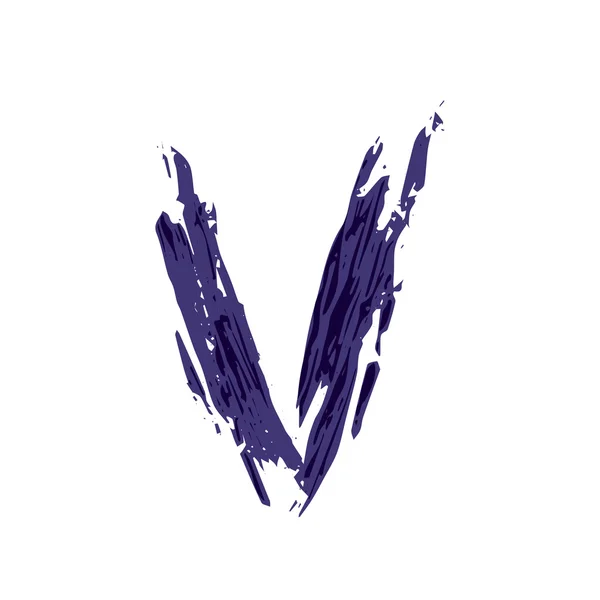
таких однородных букв на разных конструктивных началах нарушает
весь стиль шрифта независимо от того, по какому принципу скон¬
струированы все остальные буквы с округлыми элементами.
Как известно, уже в эпоху Возрождения создавалось много трак¬
татов по конструированию шрифтов разных рисунков и стилей. Осо¬
бое внимание по праву обращалось на шрифты типа антиквы. В дан¬
ной книге приведены некоторые образцы конструирования букв
великими мастерами прошлого. В дополнение к ним дается несколько
других примеров, исполненных с учетом как опыта мастеров прош¬
лого, так и практических требований современности.
abcdefßhijk Im
abcdef&h ijkt
Два принципа исполнения шрифта — два типа инструментов. Вверху — шрифт,
написанный ширококонечным пером, внизу — рисованный шрифт.
В соответствии с этим расположены и орудия выполнения:
1 — гусиное или тростниковое перо; 2 — металлическое ширококонечное перо;
3 — ширококонечное перо для выполнения крупного шрифта; 4 — плоская
кисть; 5 — перо из дерева; 6 — тонкое перо; 7 — остроконечная кисть;
S — игла; 9 — штихель
Наиболее распространенный способ конструирования шрифта —
построение букв в квадрате.
Для примера составим конструкцию ан¬
тиквы. Прежде всего установим, какую часть стороны квадрата зай¬
мет основной штрих, т. е. определим светлоту шрифта. За толщину
основного штриха примем Vio стороны квадрата. Это будет единицей
измерения основного штриха для всех букв алфавита. Затем разде¬
лим все стороны квадрата на 10 равных частей и вычертим сетку. Она
поможет конструировать буквы и следить за расположением отдель¬
ных элементов. Толщина соединительных штрихов составляет опре¬
деленную часть толщины основного штриха, например, Ч->, ‘/з и т. д.
В настоящей книге помещено несколько алфавитов рубленого
(гротескового) шрифта, сконструированных при помощи сетки (стр.
152—153). Буквы упрощенной антиквы сконструированы по тем же
принципам, но сетка не показана (стр. 144—145). Здесь в компоновке
букв важную роль играют круги разного диаметра (Vio, 2/ю или 3/ю
стороны квадрата). С помощью тех же кругов образуются и засечки.
Шрифт можно построить и на основе различных прямоугольни¬
ков, ромбов и других фигур; в зависимости от этого получим буквы
узкие или широкие, прямые или наклонные.
Во всех этих случаях
правила те же, что и при построении шрифта на основе квадрата.
Edo
Edo — это шрифт, напоминающий японскую каллиграфию сухой кистью. Этот шрифт бесплатен для личного использования, но создатель может разрешить коммерческое использование на основе сообщения, поэтому обязательно свяжитесь с ним, если вы хотите использовать этот шрифт для коммерческого проекта.
Правдивая ложь
Этот сценарий кисти напоминает названия боевиков 1990-х годов и доступен для личного использования.